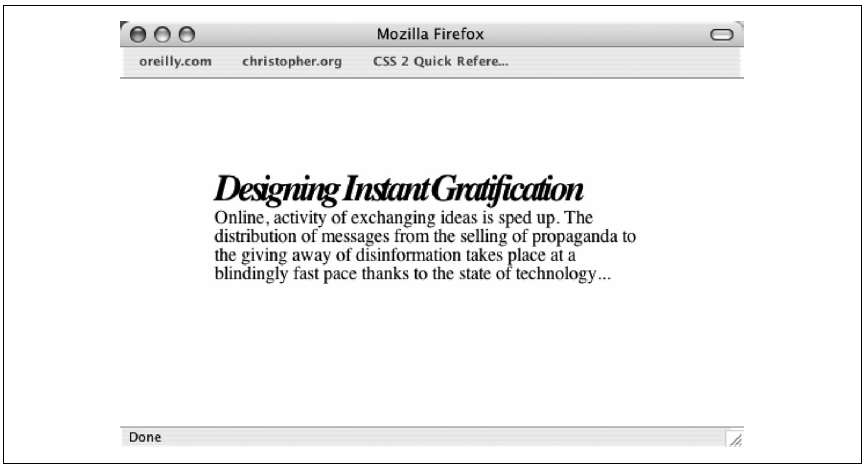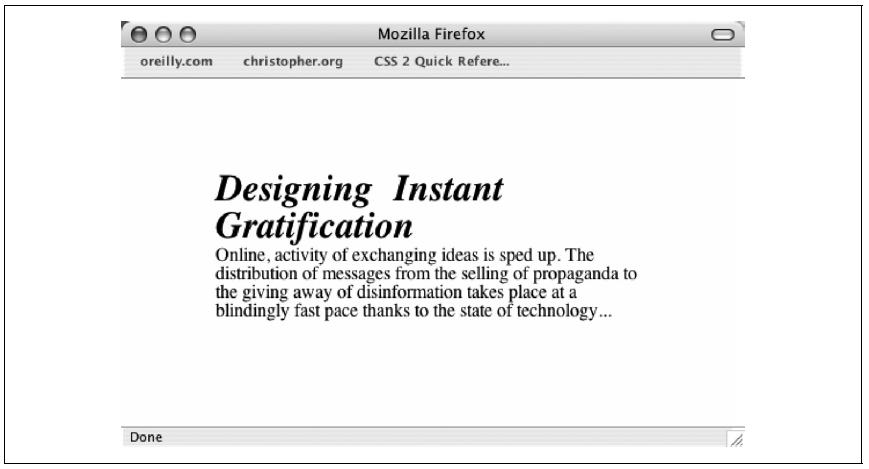
Den Abstand zwischen Buchstaben und Wörtern anpassen
Problem
Sie wollen den horizontalen Abstand zwischen Buchstaben und Wörtern (die Laufweite) im HTML-Text anpassen (siehe folgende Abbildung).
Abbildung: Standardabstand zwischen Buchstaben und Wörtern im HTML-Text.
Lösung
Den Abstand zwischen Buchstaben können Sie mit der Eigenschaft letter-spacing einstellen (siehe nächste Abbildung):
Abbildung: Für die Überschrift wurde der Abstand zwischen den Buchstaben verkleinert.
Um auch den Abstand zwischen den Wörtern einer Zeile zu verändern, verwenden Sie die Eigenschaft word-spacing (siehe nächste Abbildung):
Abbildung: Der Wortabstand in der Überschrift wurde erhöht.
Diskussion
Eine der größten Stärken von CSS liegt in der Fähigkeit, mit Typografie für das Web umzugehen. Früher mussten Webdesigner ein erschreckendes Arsenal von verschachtelten b-Elementen und Ein-Pixel-GIFs einsetzen, um den Text ansprechend aussehen zu lassen. Mit CSS dagegen sind Dinge wie die Anpassung des Abstands zwischen Buchstaben und ganzen Wörtern eines Absatzes kein Problem mehr.
Die Anpassung der Laufweite für eine bessere Ästhetik ist eine alte Tradition im Grafikdesign. Zwei Fachbegriffe beschreiben die im Text vorgenommenen Abstandsänderungen: Unterschneidung (Verringern der Laufweite, auch Kerning genannt) und Spationierung (Vergrößern der Laufweite, auch Sperren genannt). In der Praxis kommt vor allem die Unterschneidung zum Einsatz.
Die Unterschneidung beschreibt die Reduzierung des Leerraums zwischen zwei Buchstaben, um eine bessere Lesbarkeit zu erreichen. Ein Beispiel für die Unterschneidung ist die Verringerung des Abstands zwischen einem großen T und einem folgenden kleinen i. Wird die Laufweite über mehrere Textblöcke hinweg reduziert, spricht man auch von Tracking.
Es wird allgemein als Best Practice angesehen, für Werte von letter-spacing und word-spacing relative Längeneinheiten anstelle von absoluten zu verwenden. Der Hintergrund dafür ist, dass Benutzer die Schriftgrößen im Browser selbst verändern können. Ein fester Abstand von 5 Punkt zwischen zwei Buchstaben mag bei einer Schriftgröße von 12 Pixel gut aussehen. Hat ein User aber seine Schriften stark vergrößert, wird der Abstand zwischen den Buchstaben bei der Verwendung absoluter Angaben trotzdem mit 5 Punkt dargestellt. Wird die Schrift bespielsweise mit einer Größe von 72 Pixeln angezeigt, ist eine Unterschneidung von 5 Pixeln kaum noch wahrzunehmen. Bei der Verwendung relativer Einheiten wie em wird die Unterschneidung dagegen im Verhältnis zur tatsächlichen Schriftgröße berechnet. Ein Wert von 1.5em skaliert also zusammen mit dem übrigen Text.
Entsprechendes gilt für die Verwendung anderer Texteffekte. Effekte sollten so verwendet werden, dass der Text weiterhin lesbar bleibt. Wenn Ihnen die Kommunikation mit Ihren Kunden wichtig ist, ist es sinnvoller, die Effekte subtil einzusetzen. Unlesbarer Text kann viele Leute verärgern, die Sie eigentlich auch ansprechen möchten.
Die Eigenschaften letter-spacing und word-spacing werden von allen modernen Browsern unterstützt.